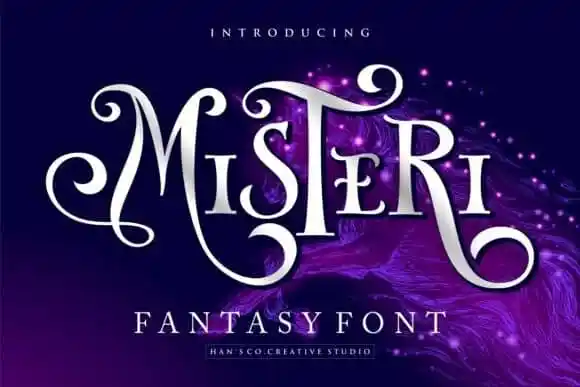
Misteri Display Font – Download Grátis
A Misteri Display Font é uma elegante escolha para projetos que exigem destaque visual. Desenvolvida pelo designer HansCo na plataforma 99designs, essa fonte tipo display serif possui um delicado e sofisticado charme. O recurso principal desta fonte é sua elegância misteriosa, com suas curvas suaves e ligaduras que conferem ao texto uma atmosfera fascinante e versátil. Perfeita para projetos como gráficos de Instagram, scripts góticos ou qualquer arte criativa inspirada em magia, a Misteri Display Font transformará ideias inusitadas em verdadeiros trabalhos de arte. Com seus traços delicados e sua capacidade única de dar ao texto uma aura mágica, esta fonte não apenas destaca seu conteúdo, mas também adiciona um toque de encanto à qualquer projeto gráfico. Ela é ideal para aqueles que desejam adicionar um elemento misterioso e sofisticado a seus projetos. Com a Misteri Display Font, você pode transformar simples ideias em verdadeiros trabalhos de arte elegantes e versáteis.